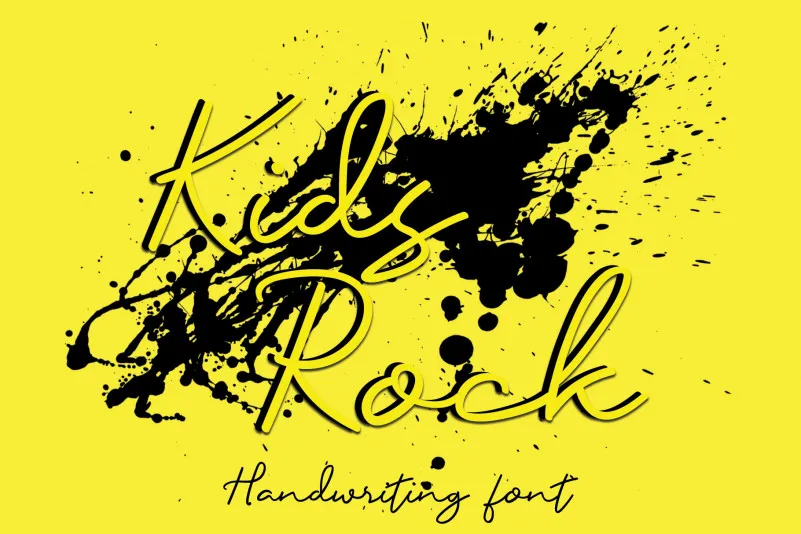
A font Kids Rock é uma criação do Erik Studio que se destaca por ser uma fonte relaxada, cíliar e leve, criando um estilo script suave. Este tipo de font oferece ao designer uma ferramenta versátil para personalizar textos em diferentes tópicos. Seja você designer gráfico, educador ou profissional de mídia, a Kids Rock está aqui para tornar sua obra mais atraente e única. Com seu estilo relaxado, é fácil incorporar este elemento ao seu projeto sem comprometer a legibilidade, garantindo que se torne um recurso valioso em sua biblioteca de fontes. Esta font foi projetada especialmente para criar textos com personalidade, tornando-a uma escolha irresistível para designers buscando dar um toque único à suas criações.